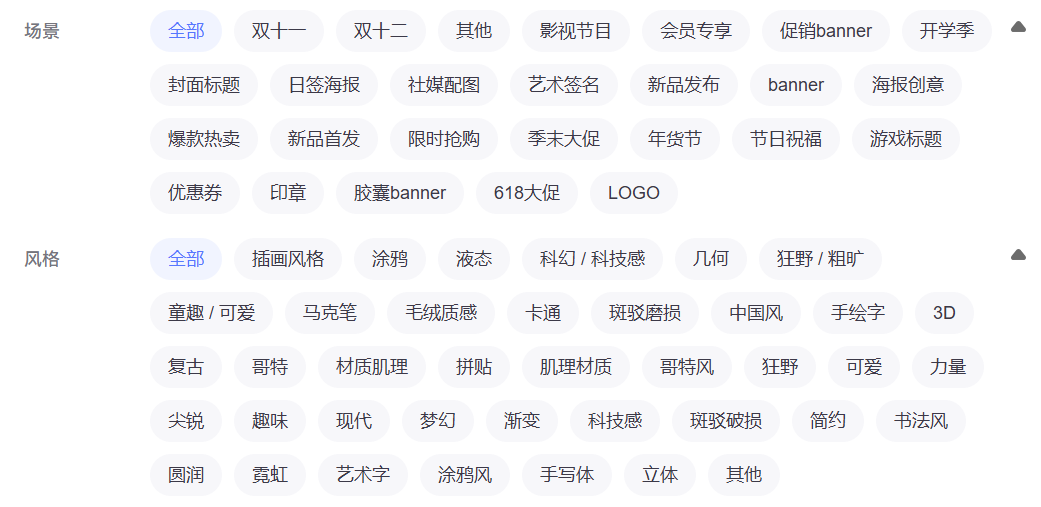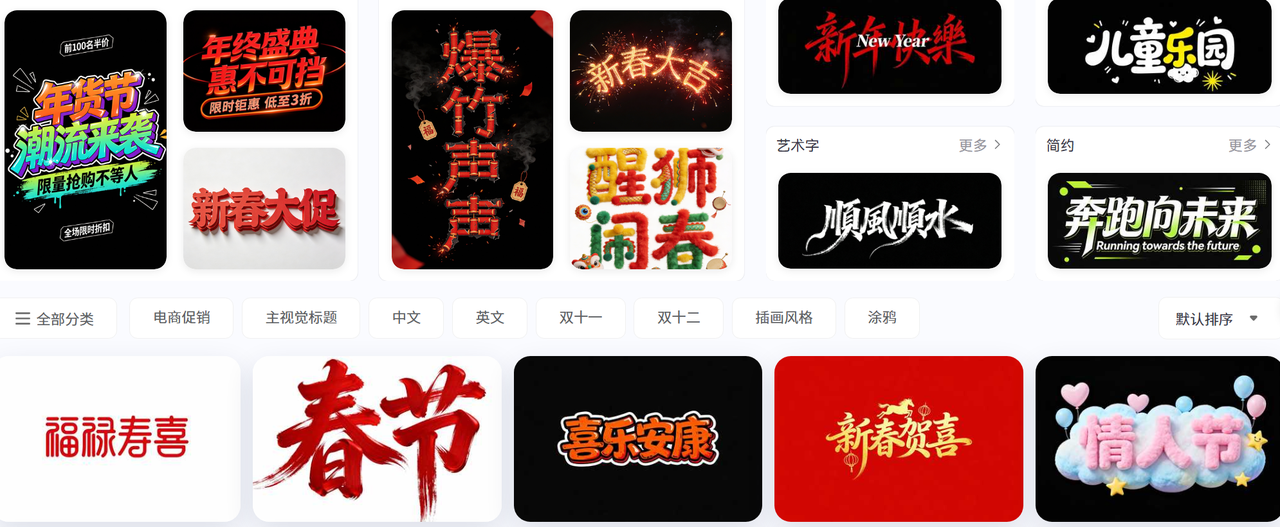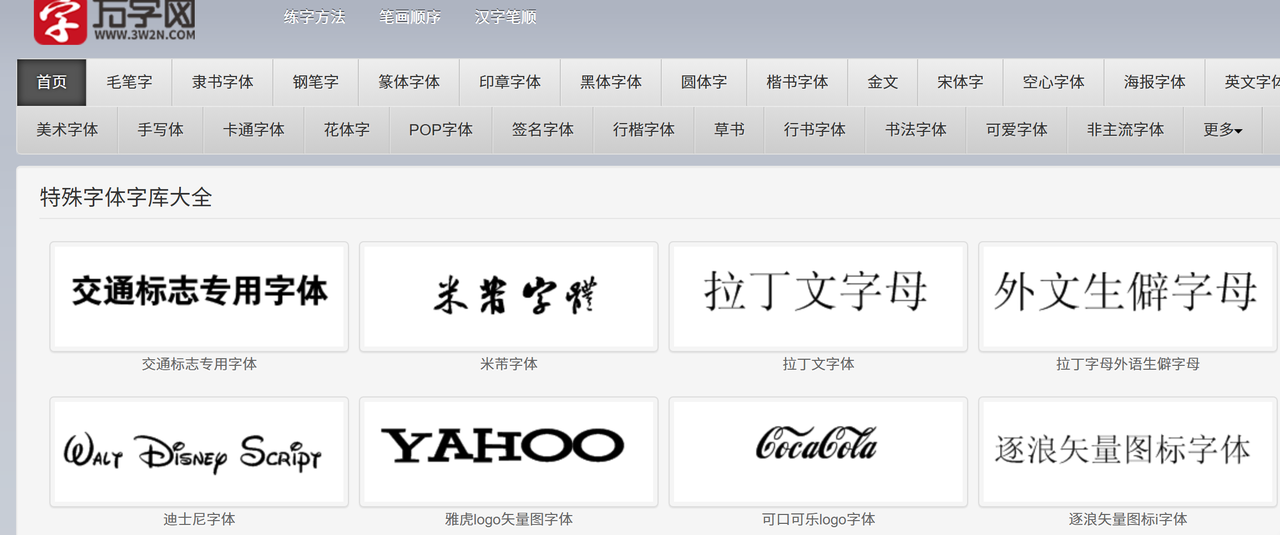
4个艺术字体在线生成网站推荐,零基础也能做设计
当下设计场景越来越多元,从朋友圈配图到海报制作,独特的艺术字体总能让画面瞬间吸睛。很多人觉得艺术字设计门槛高、需要专业技巧,其实零基础也能轻松上手,本文就为大家推荐 4 个超实用的艺术字体在线生成网站,打开浏览器就能用,输入文字、挑选风格、一键生成,全程3步搞定,哪怕是第一次接触设计,也能做出惊艳的艺术字体。
一、字由网
说到艺术字体在线生成,我最常用的就是字由网,它不仅能快速生成各类艺术字体,更有一个“黑科技”功能——AI字体识别,完美解决了“看到好看的字体却不知道名字”的痛点。
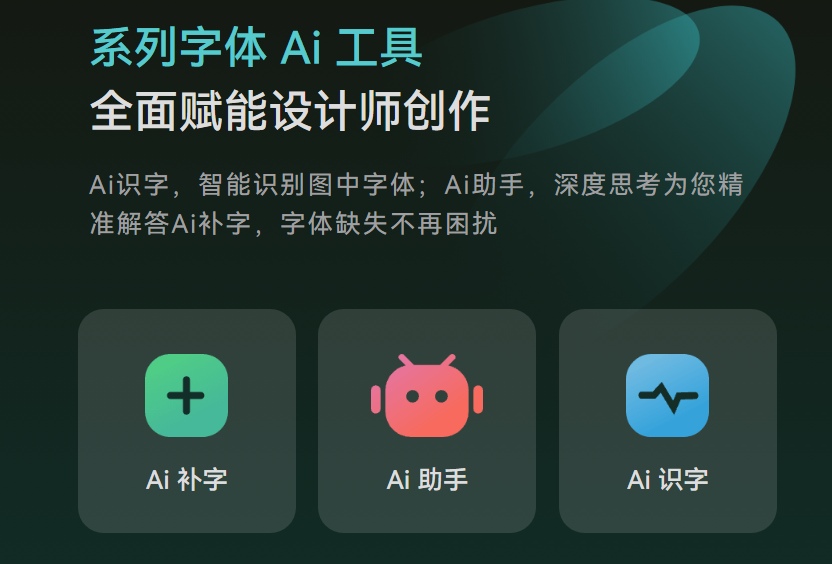
而且字由网的风格分类非常明确,能快速筛选出自己想要的艺术字体风格。
不同于其他网站只侧重“生成”,字由网实现了“识别+生成+应用”一体化,操作简单到不用看教程。比如现在临近春节,我需要生成一些与春节相关的艺术字体。可以直接选择想要的风格模板,套用更改文字就可以了。
生成艺术字体时,只需打开想要的模板,在右侧的输入框中键入需要生成的文案,点击“立即生成”,等待几秒就能得到同款效果艺术字体,还可以添加简单字体特效,满足基础设计需求。
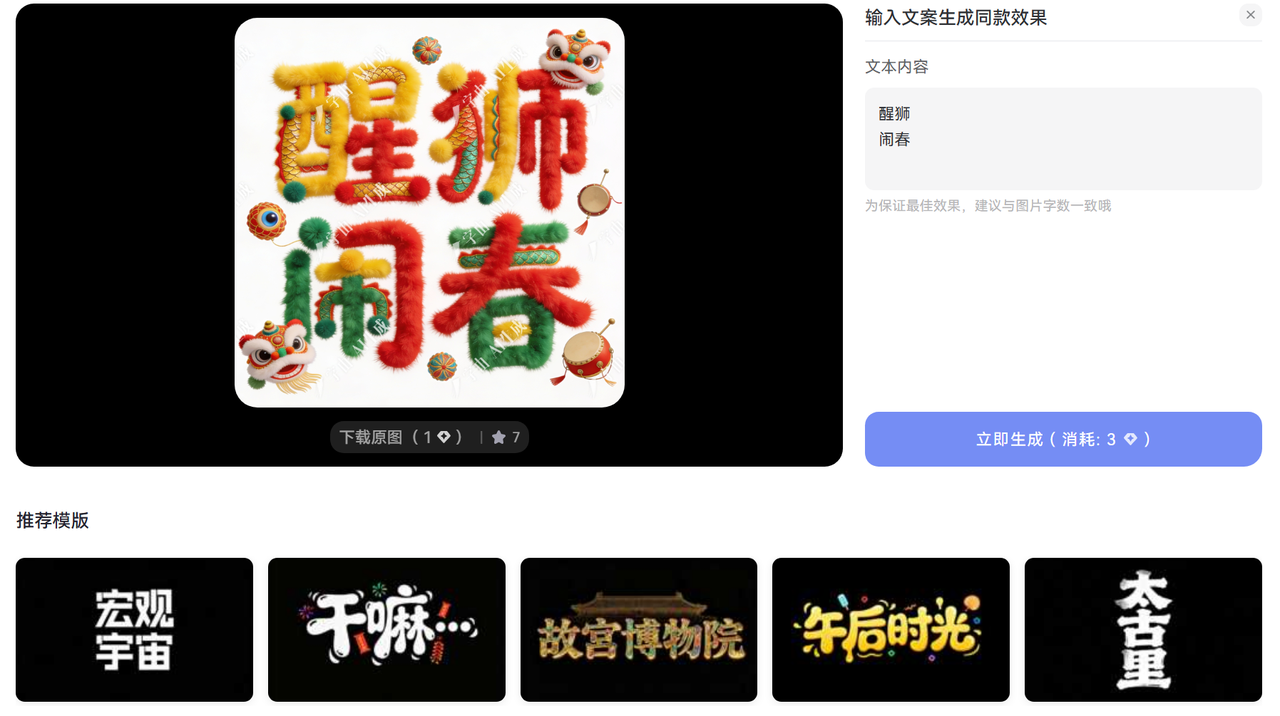
对于零基础小白来说,不用安装复杂软件,不用学习设计技巧,仅凭字由网就能解决大部分艺术字体相关的设计难题,性价比超高。
二、万字网
万字网是一款兼顾艺术字体生成和书法学习的宝藏网站,字体资源丰富且主打书法风格转换,深受书法爱好者、老师和学生喜爱,堪称“在线书法字典+练字神器”,既适合做字体设计,也适合日常练字参考。它并非具备完全的艺术字体生成功能,但包括很多艺术字体或者特殊字体的模板,用来做设计也十分方便。
三、艺术字网
艺术字网站操作简单,一打开网页可以直接输入文字,可选择字体风格,重点是“特效控制台”,能一键添加渐变颜色、文字倒影、立体效果、阴影,还能调整特效强度,不用自己手动调试,生成的字体自带高级感它的字体生成后,支持右键保存图片,可直接用于各类设计场景,无需额外编辑。
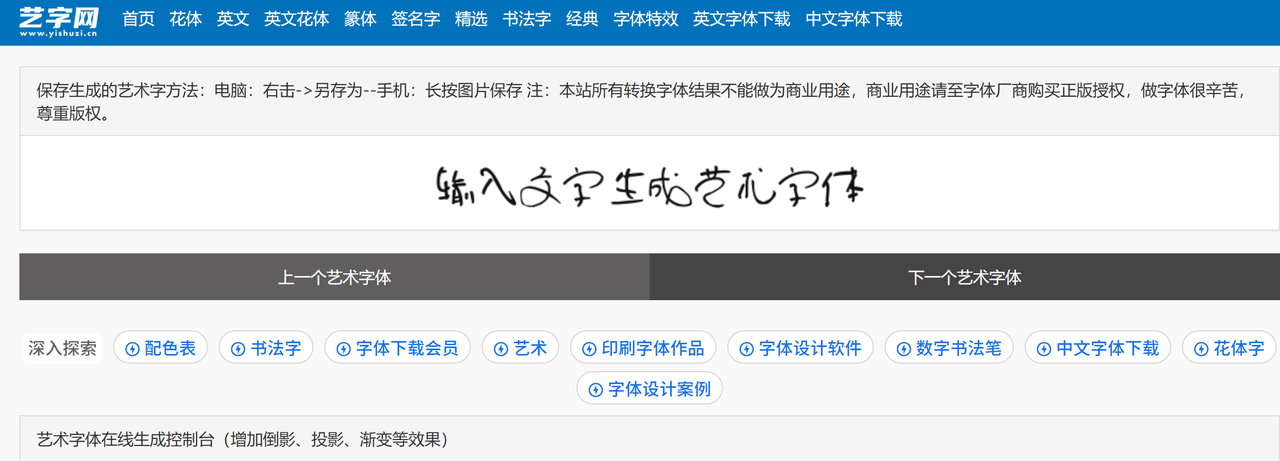
四、字体天下
最后一个推荐的是字体天下,既有适合小白的免费艺术字体生成功能,也有适合设计师的正版商用字体资源,是一个综合性的字体服务网站,实用性和安全性都很出色。作为小白,我们可以用它的在线艺术字体生成功能,操作简单,输入文字、选择字体、一键生成,支持调整字体大小、颜色,字体风格涵盖简约、复古、卡通、英文等,满足个人设计需求。
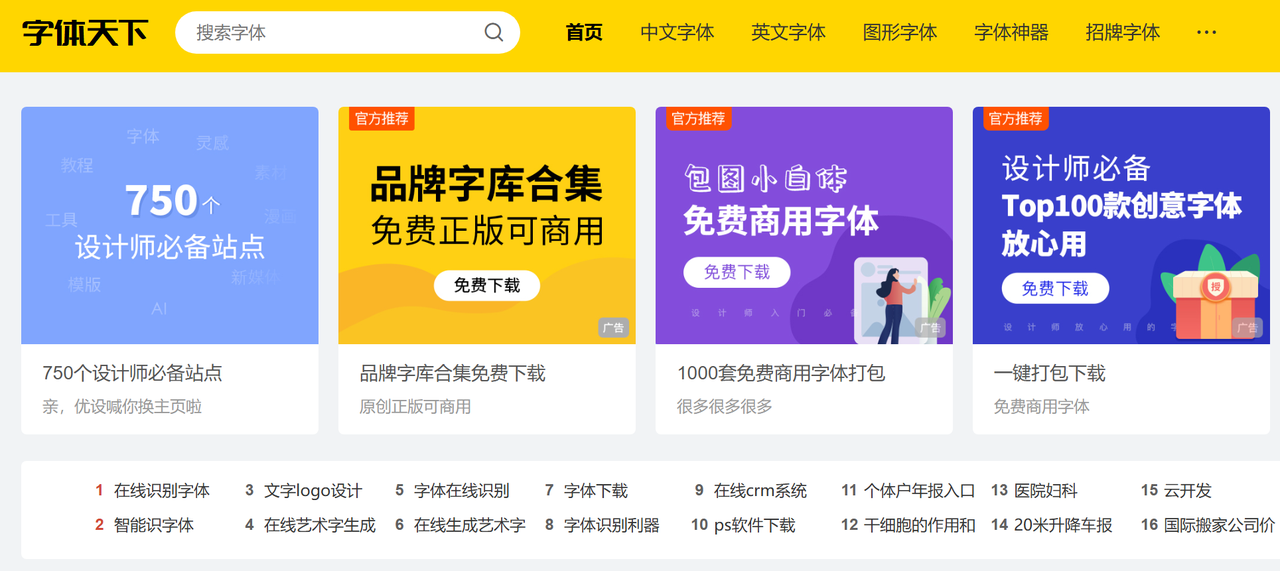
其实,零基础做设计,不用追求复杂,选对工具就能事半功倍。不用花费大量时间学习设计技巧,不用花钱购买昂贵的字体素材和设计软件,打开浏览器,输入文字、一键生成,就能拥有专属艺术字体,轻松解锁设计乐趣,让每一份设计都更有质感、更有特色。